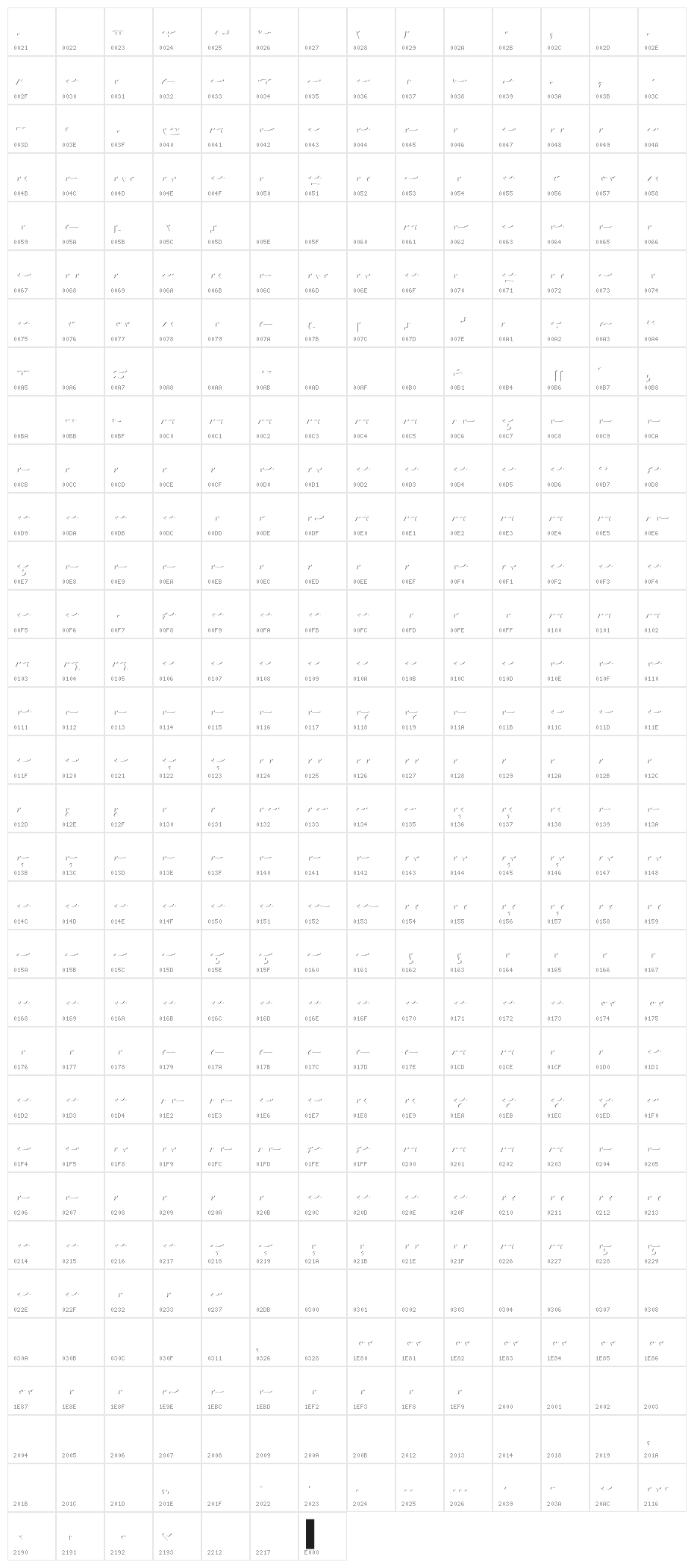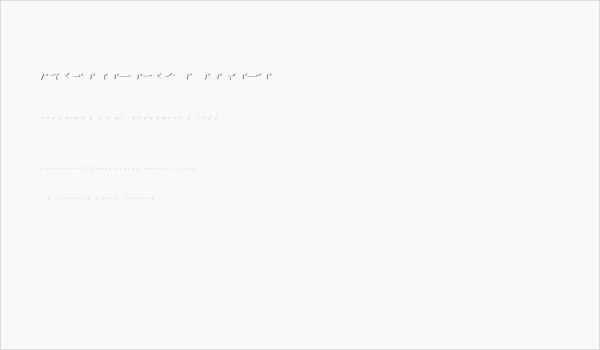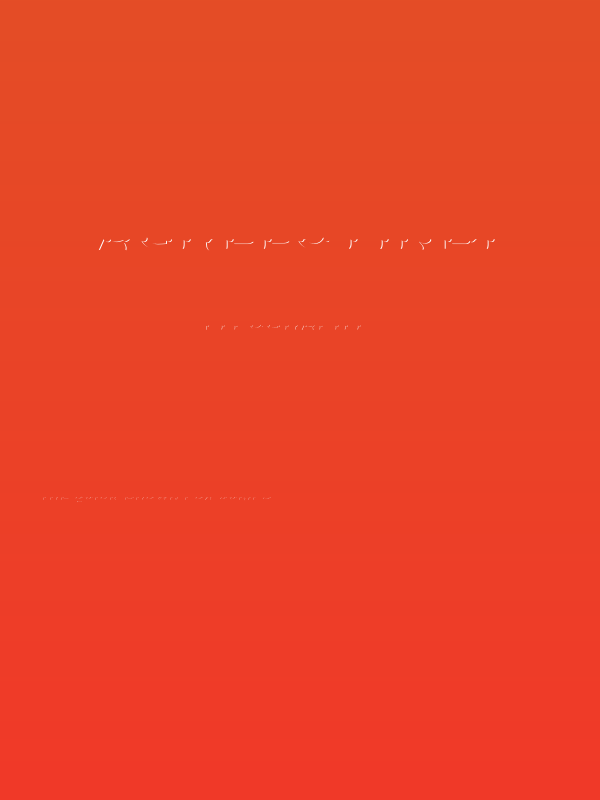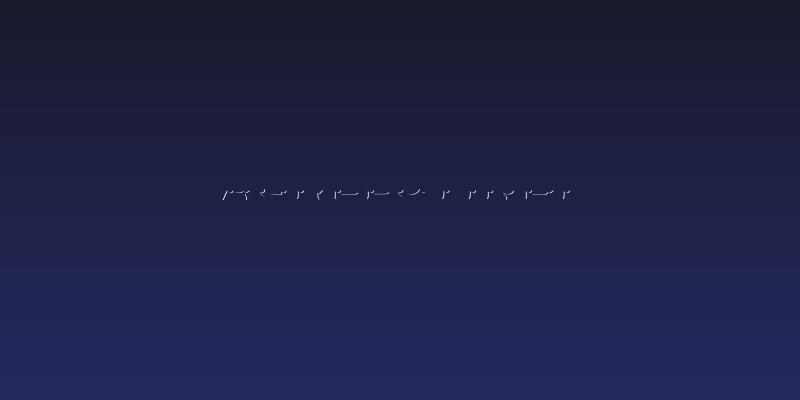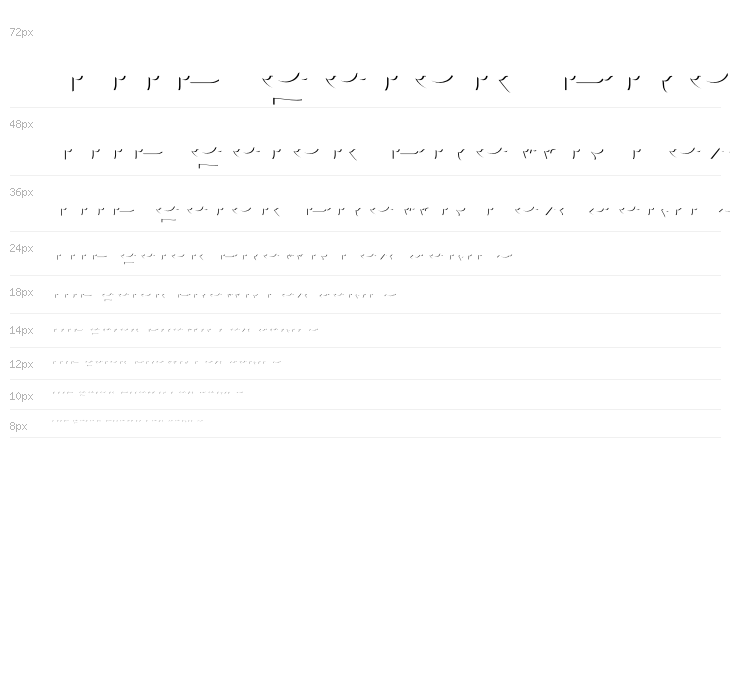
AgreloyInB1 Font
✎ Curly
| Categorie | Curly |
| Caso d'uso | Logos, Artistic projects, Posters |
| Progetti proposti | Ideal for creative projects such as art installations, modern branding, expressive posters, and avant-garde designs. |